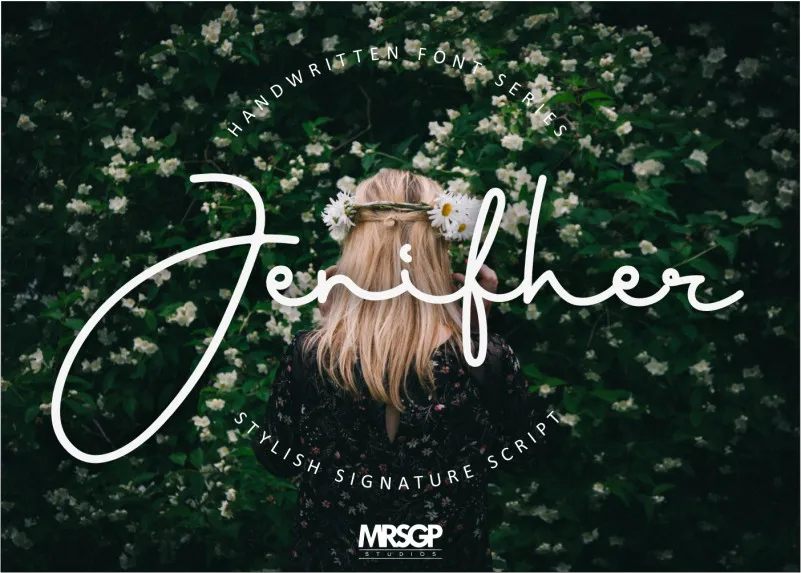
Jenifher Signature Script Font – Download Grátis
Aqui está uma versão envolvente e natural dos dois parágrafos curtos para a descrição do download da font ‘Jenifher Signature Script Font’: Este é um belo exemplo de texto gráfico handwritten que inspira e enriquece suas criações digitais. A Jenifher Signature é uma fonte criada com cuidado, repleta de suaves curvas e traços levemente gentis. Ela foi projetada para proporcionar um toque de personalidade original a qualquer projeto. Esta font naturalmente adere a seus trabalhos de marcação ou identificação visual, sendo perfeitamente adequada para aplicativos como branding, logotipos, anúncios, embalagens de produtos, design fotográfico e até mesmo para criações em papel. A Jenifher Signature é sua companheira perfeita em qualquer projeto que precise de um toque autêntico da escrita manual. Com o designer Hamilton e seu estúdio MRSGP Studios ao seu lado, você pode contar com um produto cuidadosamente pensado para atender à sua necessidade de design. Estamos confiantes de que você vai apreciar a elegância e a personalização que esta font pode oferecer em seus trabalhos.